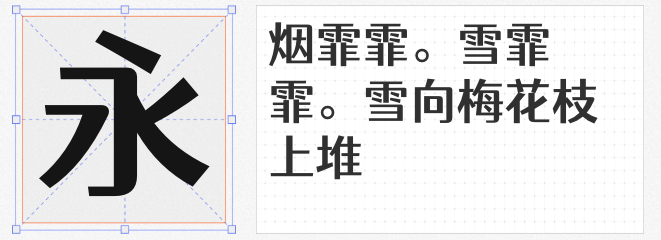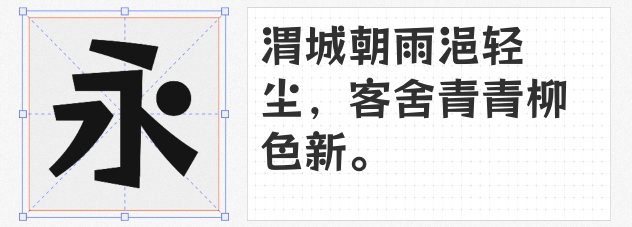
在设计中,标题字体是视觉焦点的核心,需兼顾辨识度与风格表达。以下四款免费商用字体以独特的设计语言,为标题设计提供多元化选择,助力设计师轻松打造吸睛视觉。
仓耳非白 W04 以强烈的粗细对比与方整结构脱颖而出。设计师通过加粗主笔画强化“黑”的视觉重量,同时以纤细线条勾勒“白”的留白空间,形成张力十足的视觉层次。字形转折处统一采用直角处理,撇捺以直线表现,赋予字体硬朗的工业感;而圆形点笔的加入,则巧妙中和了锐利感,使整体结构在刚硬中透出一丝柔和。这款字体适合科技、运动或潮流类标题设计,其独特的几何美学能快速抓住观众注意力。
仓耳渔阳体 W04 融合了宋体的典雅与黑体的现代感,笔画转折处采用圆角设计,既保留了传统字体的文化底蕴,又增添了轻盈的灵动气质。其结构厚重而不笨拙,横细竖粗的笔画对比适度,适合文化、艺术或生活类标题设计。圆角的处理让字体在视觉上更显友好,尤其适用于需要传递温暖或人文气息的场景。
法棍体以“纤细如法棍”的笔画为特色,通过规律性加粗局部笔画,形成独特的节奏感。曲线折角的设计弱化了传统字体的严肃感,赋予其可爱而不臃肿的气质。这款字体适合甜品、儿童或时尚类标题设计,其轻盈的视觉效果能营造出清新、活泼的氛围,尤其适合搭配手绘风格或扁平化设计。
标小智龙珠体以“龙珠”元素为核心设计亮点,通过圆点替代部分笔画,使字体瞬间充满趣味性与记忆点。笔画粗细变化模拟手写笔触的力度,硬朗中带有动感,适合游戏、动漫或潮流品牌标题设计。其流行风格的字体骨架与龙珠元素的结合,既能传递年轻化的品牌态度,又能通过视觉符号强化品牌辨识度。
标题设计的关键在于“精准表达”,而这四款免费商用字体以风格化的设计语言,为设计师提供了从“刚硬几何”到“灵动圆角”、从“纤细可爱”到“动态点睛”的多元选择。无论是商业项目还是个人创作,均可通过合理运用这些字体,让标题成为传递品牌调性的视觉利器。